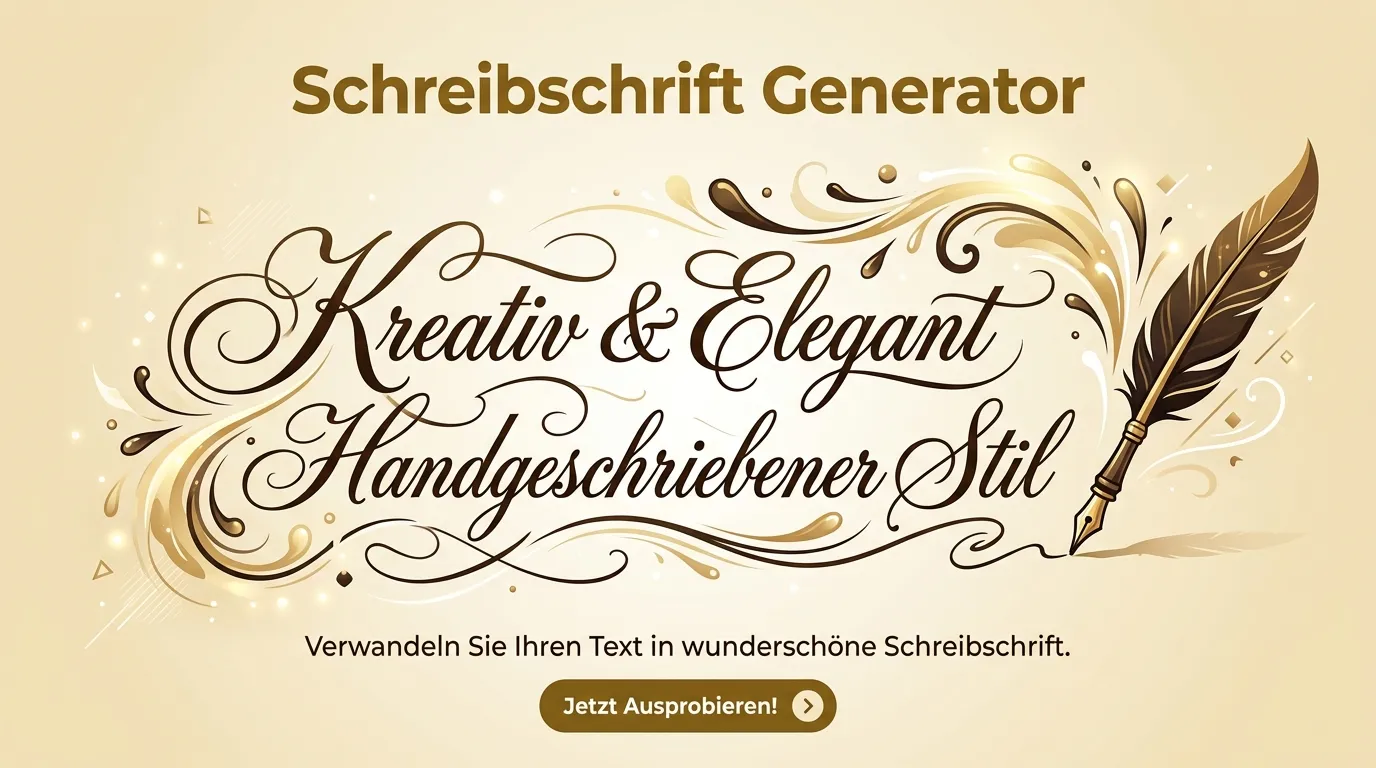
Schreibschrift Generator
Vergleich: Die Schriftarten auf einen Blick
Druckschrift
Normal, unverbunden
Kursiv
Schräg, unverbunden
Schreibschrift
Fließend, verbunden
Fraktur / Gothic
Gebrochen, historisch
Schreibschrift für Instagram, TikTok und WhatsApp
Schreibschrift verleiht deiner Instagram-Bio oder deinem TikTok-Profil eine persönliche, handschriftliche Note: und hebt dich sofort von den Millionen Profilen mit Standard-Schrift ab. Besonders beliebt sind Schreibschrift-Stile für Zitate, Mottos und Berufsbezeichnungen in der Bio.
Sütterlin, Kurrent und die Geschichte der deutschen Schreibschrift
Die deutsche Schreibschrift hat eine lange, wechselvolle Geschichte: Kurrentschrift wurde ab dem 16. Jahrhundert als Alltagshandschrift verwendet, mit spitzen, eng stehenden Buchstaben. 1911 entwickelte Ludwig Sütterlin im Auftrag des preußischen Bildungsministeriums eine einfachere Variante mit runderen Formen, die bis 1941 an deutschen Schulen gelehrt wurde.
Nach 1941 löste die lateinische Ausgangsschrift (verbundene Druckbuchstaben) Sütterlin im Unterricht ab. Heute leben diese historischen Schriften als dekorative Elemente für Branding, Tattoos und kreative Projekte weiter: und in der Ahnenforschung, wo Briefe und Urkunden in Kurrent oder Sütterlin entziffert werden müssen.
Welche Schreibschrift passt zu welchem Zweck?
Elegante Kursivschrift (𝒯ℯ𝓍𝓉) eignet sich für Hochzeitseinladungen, persönliche Nachrichten und stilvolle Bios. Fett-kursive Schreibschrift (𝑻𝒆𝒙𝒕) ist ideal für Überschriften und Call-to-Actions. Gotische Varianten passen zu Metal-Bands, Gaming und düsteren Designs. Sütterlin-Optiken sind perfekt für historische Projekte, Brauerei-Branding und traditionelles Handwerk.
Eng verwandt mit Sütterlin und Kurrent ist die altdeutsche Frakturschrift , die als Druckschrift-Pendant der historischen deutschen Handschrift dient.